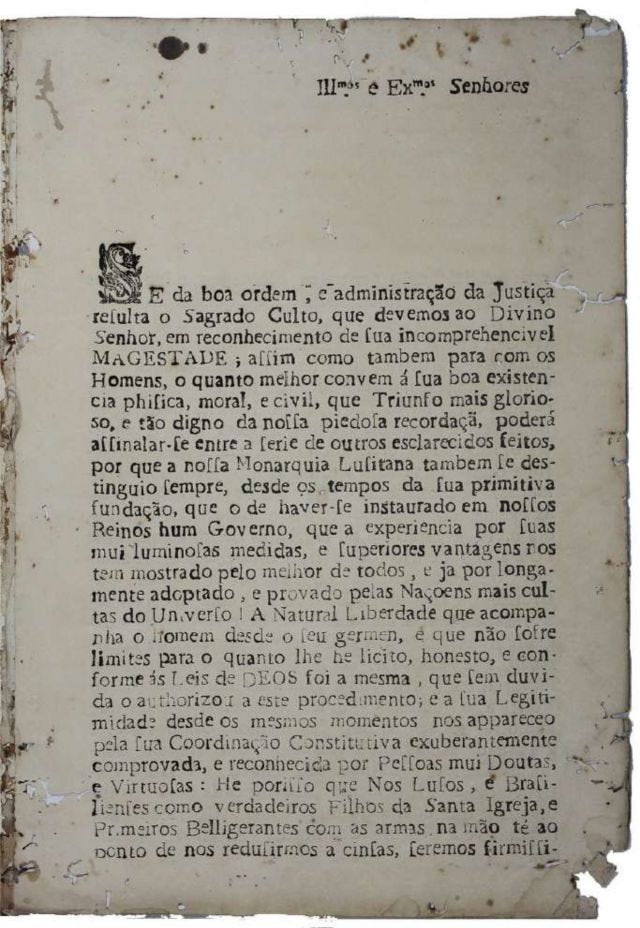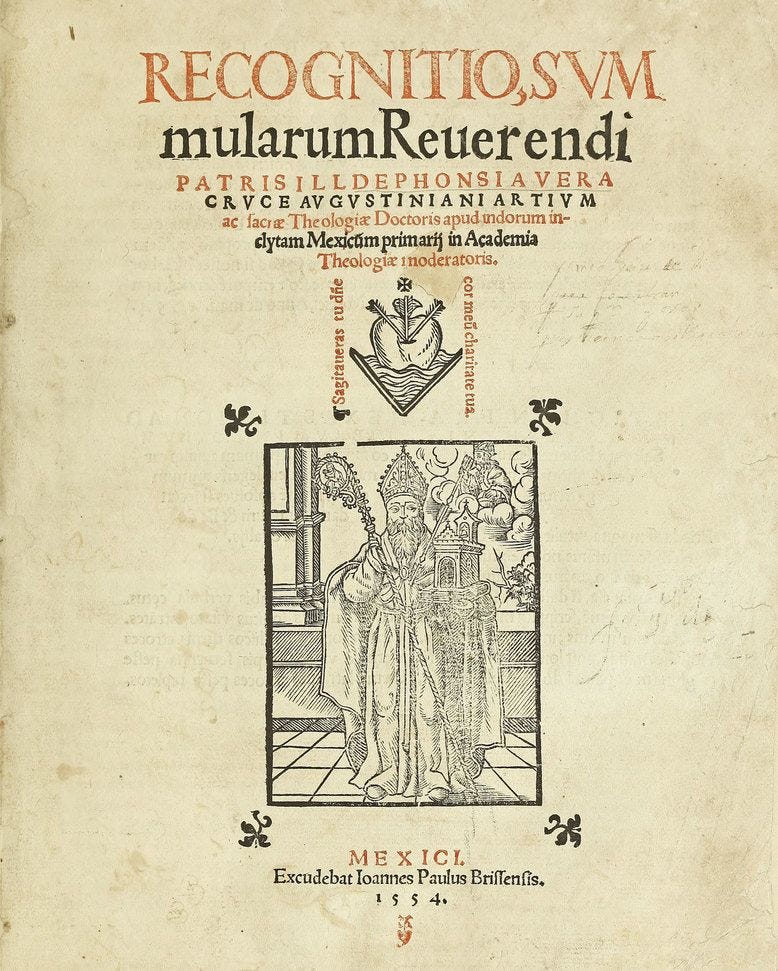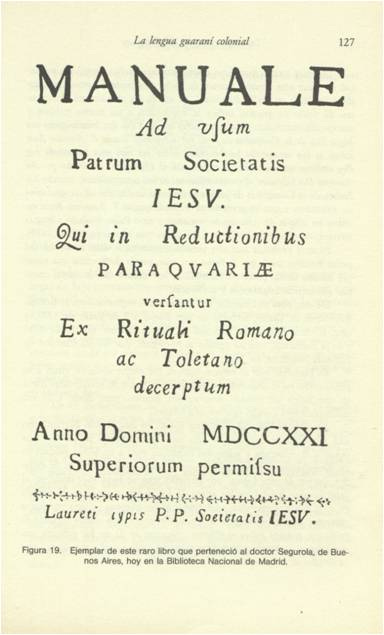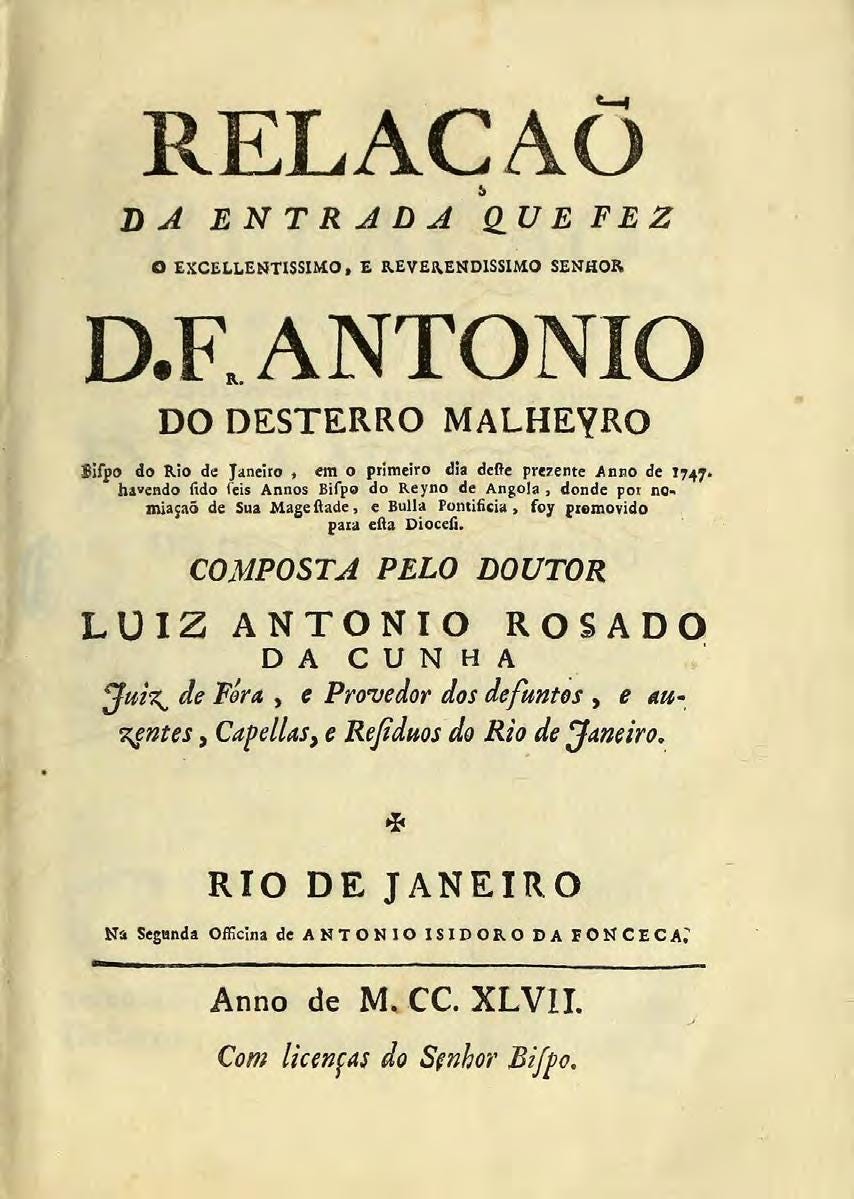
Tipo Aquilo #32 – As letras abertas da América Latina
Um dos melhores sites da Internet de todos os tempos é o Spurious Correlations, uma coleção de gráficos que relacionam contextos distintos com progressões semelhantes e correlações absolutamente não-causais. Por exemplo, apresentam progressão semelhante a quantidade de divórcios no estado norte-americano de Maine e o consumo per capita de margarina nos Estados Unidos. Nessa edição, eu começo com dois dados interessantes sobre a América Latina, e que o cruzamento deles também caracteriza uma correlação estranha, a princípio.
De um lado, temos Argentina e Chile logo à frente do Brasil entre os países com mais hábito de leitura na América Latina; do outro, temos Argentina e Chile logo à frente do Brasil em projetos selecionados na última bienal do Tipos Latinos. Se a gente olhar para como a tipografia se espalhou na América durante e após os períodos de colônia — história esta que vamos conhecer mais hoje —, dá pra entender melhor os resultados do Tipos Latinos; se você quiser partir para uma reflexão mais profunda e entender a tipografia como um elemento na formação de registros escritos e uma memória coletiva da população, e também na alfabetização, educação e propagação de cultura, a correlação fica um pouco menos estranha.
Por um certo fetiche nosso, se você perguntasse a uma pessoa não tão leiga onde foi estabelecida a primeira oficina tipográfica da América, ela diria que foi nos Estados Unidos, e estaria errada. Em verdade, a primeira prensa instalada em solo americano foi na Cidade do México, em 1539 pelo impressor lombardo Juan Pablos. Antonio Espinosa, impressor mexicano formado na Espanha, provavelmente foi o primeiro gravador de tipos do Novo Mundo: data de 1554 o Recognitio summularum, um antigo documento impresso na oficina de Juan Pablos com tipos gravados por Espinosa após seu regresso ao México. Atualmente, a imprensa de Pablos é o museu Casa de la Primer Imprenta de América.
O Peru é o segundo lugar onde se tem registro de prensas tipográficas instaladas na América, sendo instalada em Lima, 1584. Enquanto o Vice-Reino da Nova Espanha (que reunia toda a América Central e o sul e leste dos EUA) era a porção colonizada mais próxima da península ibérica, o território peruano compunha o antigo Vice-Reino do Peru, que tornou-se a maior fonte de ouro e prata explorados pela metrópole. A maior parte dos registros históricos da colonização espanhola vêm destes dois lugares.
Além do registro das atividades de exploração de ouro e prata, as imprensas coloniais tinham a função de preparar material catequético em línguas nativas para o processo “civilizatório” das populações indígenas, massacradas nos primeiros anos da colonização. As missões jesuíticas fizeram com que outros pontos das colônias erguessem universidades e, em consequência, oficinas impressoras nos séculos seguintes. Entre 1610 e 1612, foi estabelecida uma oficina de impressão nas proximidades de La Paz; no final do séc. XVII, missões instaladas no atual Paraguai, que tinham notável reputação com a fabricação de livros, adquiriram suas próprias oficinas tipográficas.
Nestas mesmas missões paraguaias, há registros de tipos móveis feitos com estanho por volta de 1703, e dois anos mais tarde, sendo usados para produzir o primeiro livro “totalmente feito na América”. Anos mais tarde, a oficina de impressão de Loreto, na Argentina, também passou a produzir impressos para evangelização das populações nativas. A Companhia de Jesus em Loreto dispunha de uma impressora móvel, que ela conseguia levar para outros pontos próximos e fazer impressões localmente; isso fez com que seus tipos sofressem grande degradação e perda de qualidade, ao ponto de que várias impressões preservadas de Loreto apresentem problemas sérios de consistência entre letras e entrelinhas. Nos anos seguintes, Bogotá (1739), Quito (1760), Nueva Valencia (Venezuela, 1764), Córdoba (1766), Santiago (1776) e Buenos Aires (1779) estabeleceram suas primeiras oficinas impressoras locais.
Acho que vocês estão sentindo falta de um certo lugar, né? Então, dizem boatos que a invasão holandesa à Capitania de Pernambuco em 1630, talvez, quizás, sais pas, tenha estabelecido uma impressão local, mas a falta de registros coloca isso no campo da mera especulação. O que existe realmente registrado é a iniciativa de Antônio Isidoro da Fonseca de montar, no Rio de Janeiro, a primeira oficina tipográfica da América Portuguesa. Em 1747, Isidoro começou a produzir alguns de seus numerosos impressos, e também em 1747, teve que fechar sua oficina por ordem da coroa portuguesa. O fechamento decorria da proibição de qualquer atividade fabril na colônia e da necessidade de exame prévio do Santo ofício sobre o conteúdo de qualquer impresso.
Isidoro nunca conseguiu uma licença real para estabelecer uma oficina impressora em solo brasileiro; apenas quando Dom João VI precisou fugir de uma invasão napoleônica à Portugal, em 1808, que o Brasil finalmente teve sua imprensa oficial. A modernização necessária para acomodar o novo status do Brasil de Reino Unido a Portugal trouxe no mesmo ano os primeiros jornais brasileiros: o Correio Braziliense, impresso em Londres, e o Gazeta do Rio de Janeiro, de imprensa nacional. O impacto da presença de impressos periódicos na sociedade brasileira é análogo à prensa tipográfica para a reforma protestante na Alemanha, em que de repente, muitas pessoas passaram a ter acesso a esse conteúdo, e novos pensamentos efervesceram nas pessoas junto com o desenvolvimento do país.
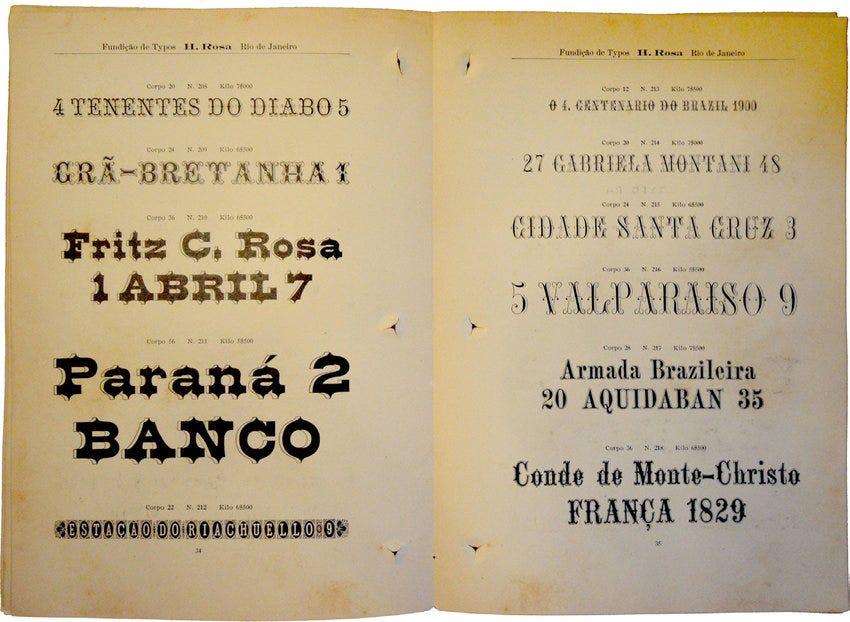
Também no séc. XIX, o Brasil abrigaria suas primeiras fundições de tipos móveis. Até a independência do Brasil, outras cidades, como Recife, Belém e Vila Rica (Ouro Preto) também tinham tipografias instaladas; depois de 1822, diversas oficinas surgiram no Brasil, o que alimentou a demanda por tipos móveis que não podiam mais depender apenas de importação. No entanto, os tipos móveis fabricados pela Typographia Americana, Fundição Franceza, Henrique Rosa e, posteriormente, Funtimod e Manig tinham seus caracteres licenciados de fontes produzidas majoritariamente na Europa.
O único registro de tipos móveis desenhados e criados no Brasil no séc. XIX é datado de 1821, em que o paraense João Francisco Madureira apresenta uma solicitação ao governo do Grão-Pará para que pudesse imprimir e produzir tipos em sua oficina. O grande detalhe dessa solicitação, como eu contei lá na primeira edição, é que ela foi composta e impressa por tipos produzidos pelo próprio Madureira, com desenhos de letras originais. Apesar de tamanha inventividade, ele nunca conseguiu licença oficial para o exercício de tipógrafo no Brasil.